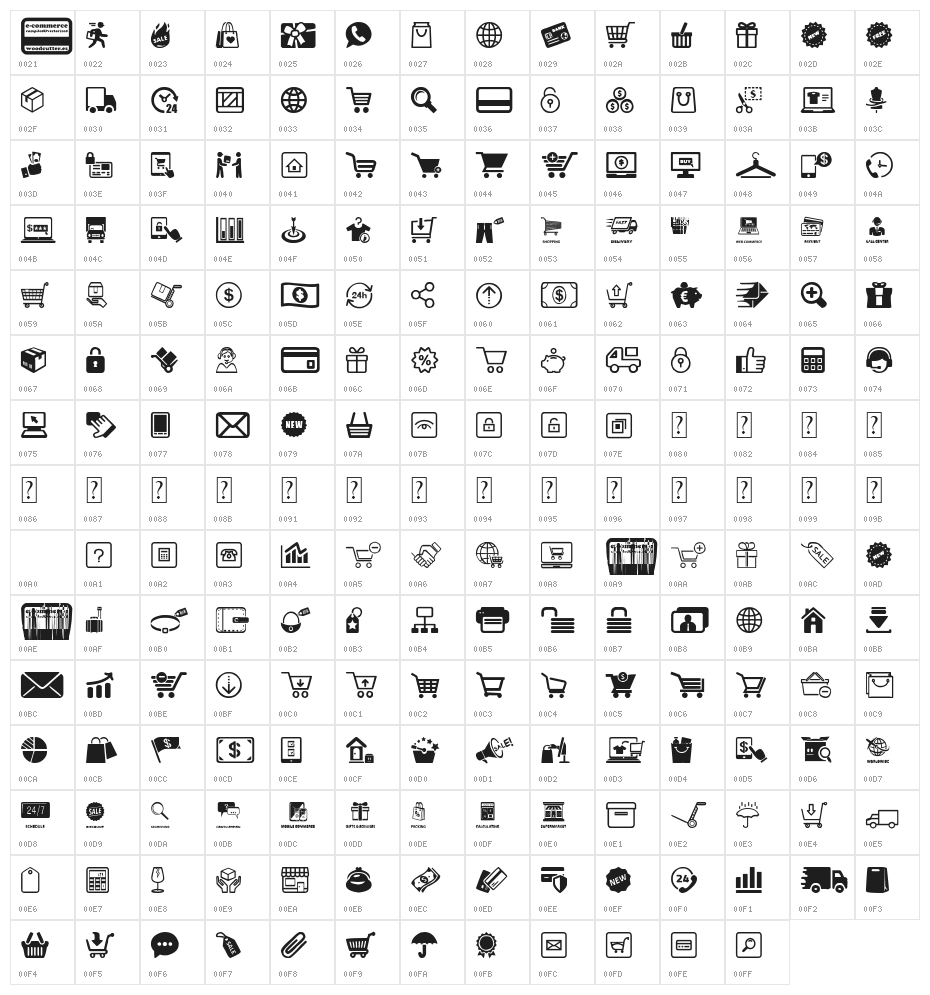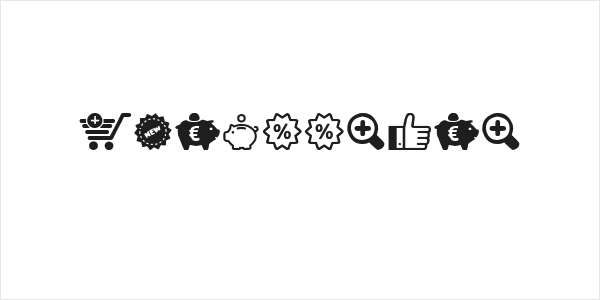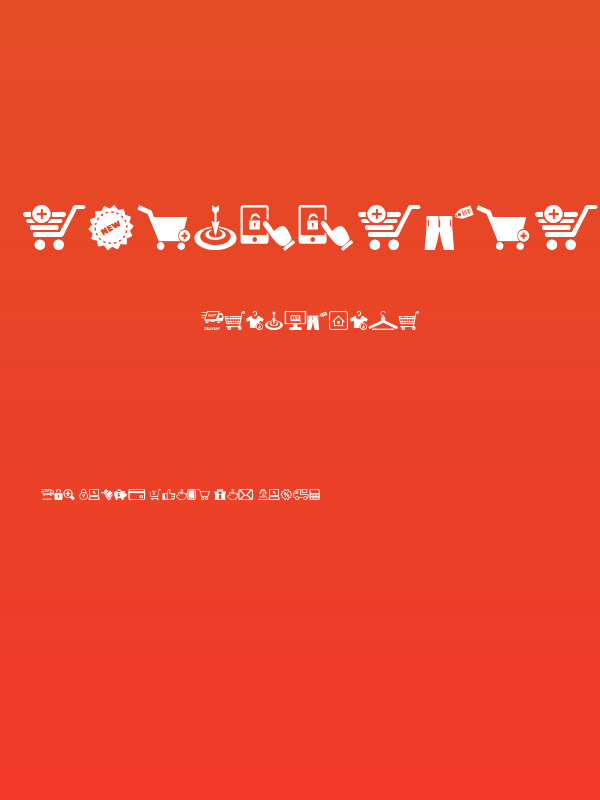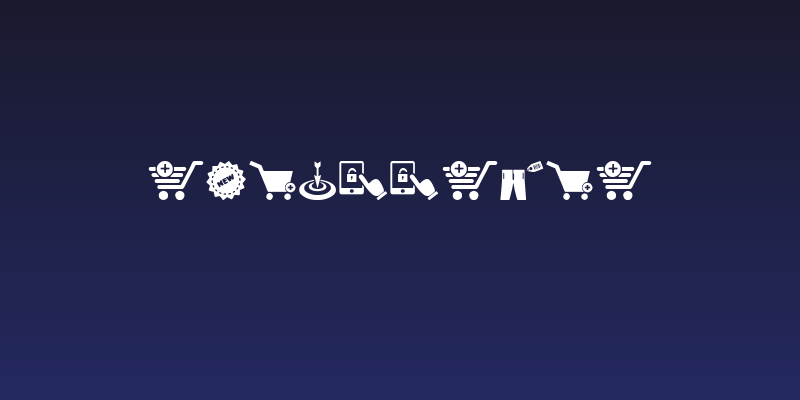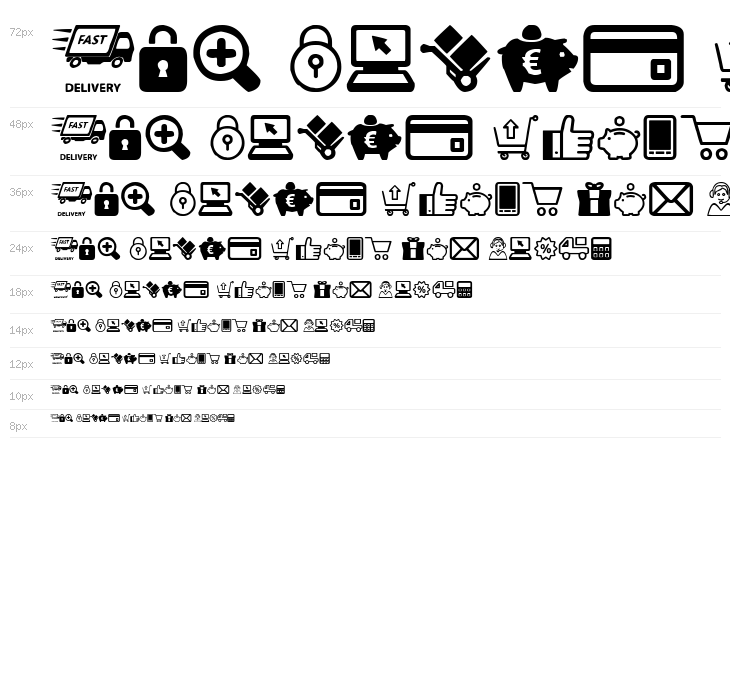
E-commerce Font
✎ Dingbats
| Style général | Modern, Functional, Minimalist |
| Cas d'utilisation | Icons for digital interfaces, navigation, and branding in e-commerce contexts. |
| Projets proposés | E-commerce websites, mobile apps, online store dashboards, promotional materials, infographics. |